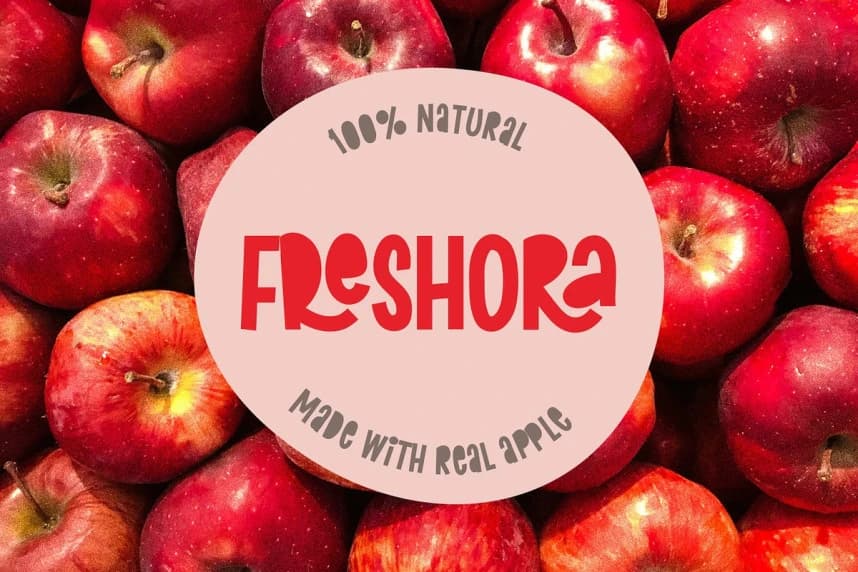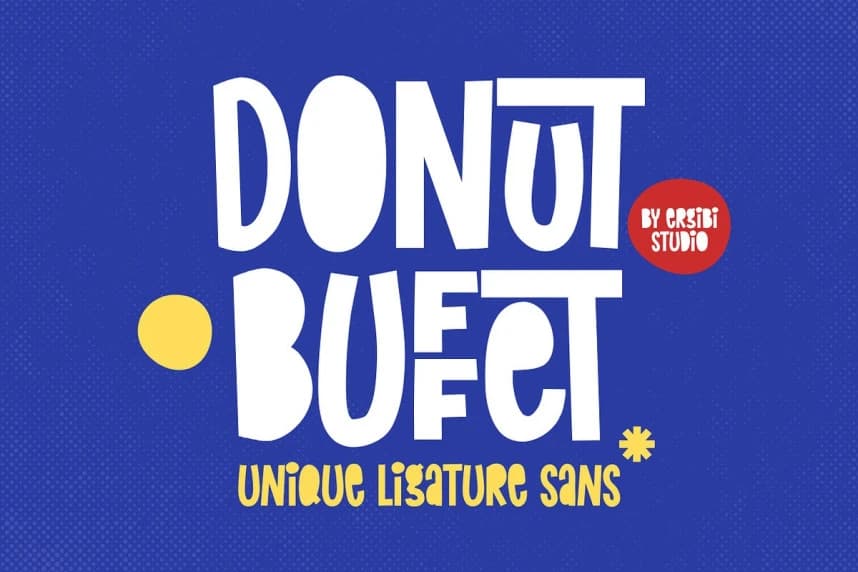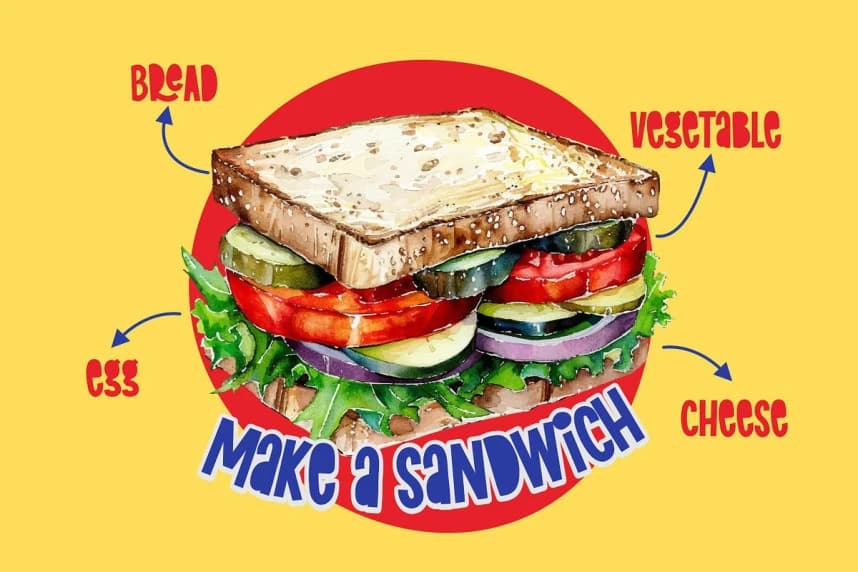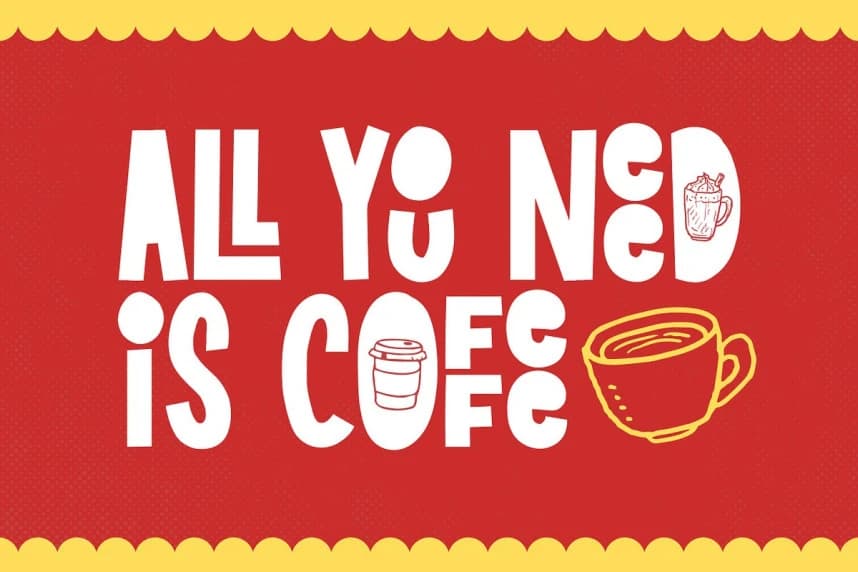
Donut Buffet Font
Donut Buffet Font, eğlenceli ve ifade gücü yüksek tasarım projeleri için tasarlanmış, garip ve benzersiz bir sans-ugly fontudur. Logotipler, filigranlar, afişler, marka materyalleri, promosyonlar, ürün ambalajları ve daha fazlası için mükemmeldir — bu font, her harf formuna kasıtlı olarak bir “çirki
Donut Buffet Font, eğlenceli ve ifade gücü yüksek tasarım projeleri için tasarlanmış, tuhaf ve benzersiz bir sans fontudur. Logotipler, filigranlar, posterler, marka materyalleri, promosyonlar, ürün ambalajları ve daha fazlası için mükemmeldir — bu font, her harf biçimine kasıtlı olarak “çirkin” bir çekicilik getirir.